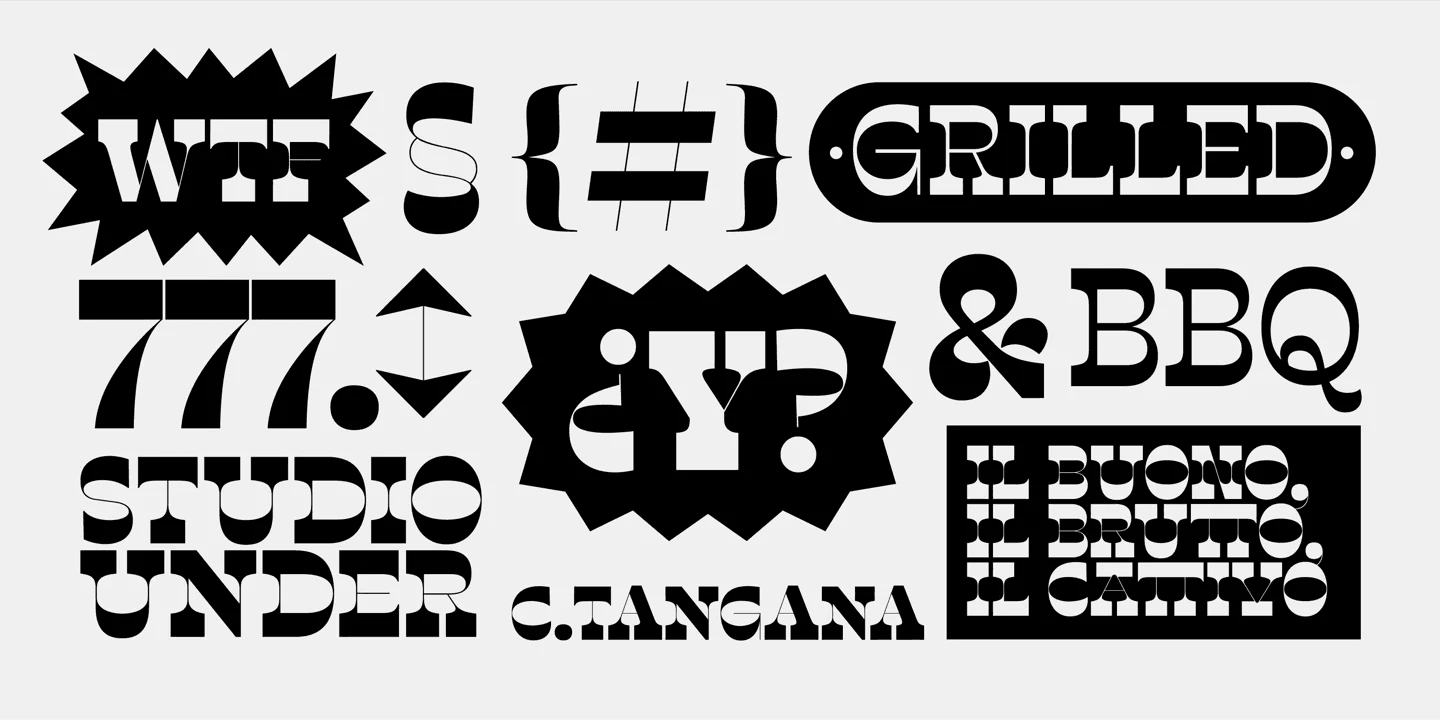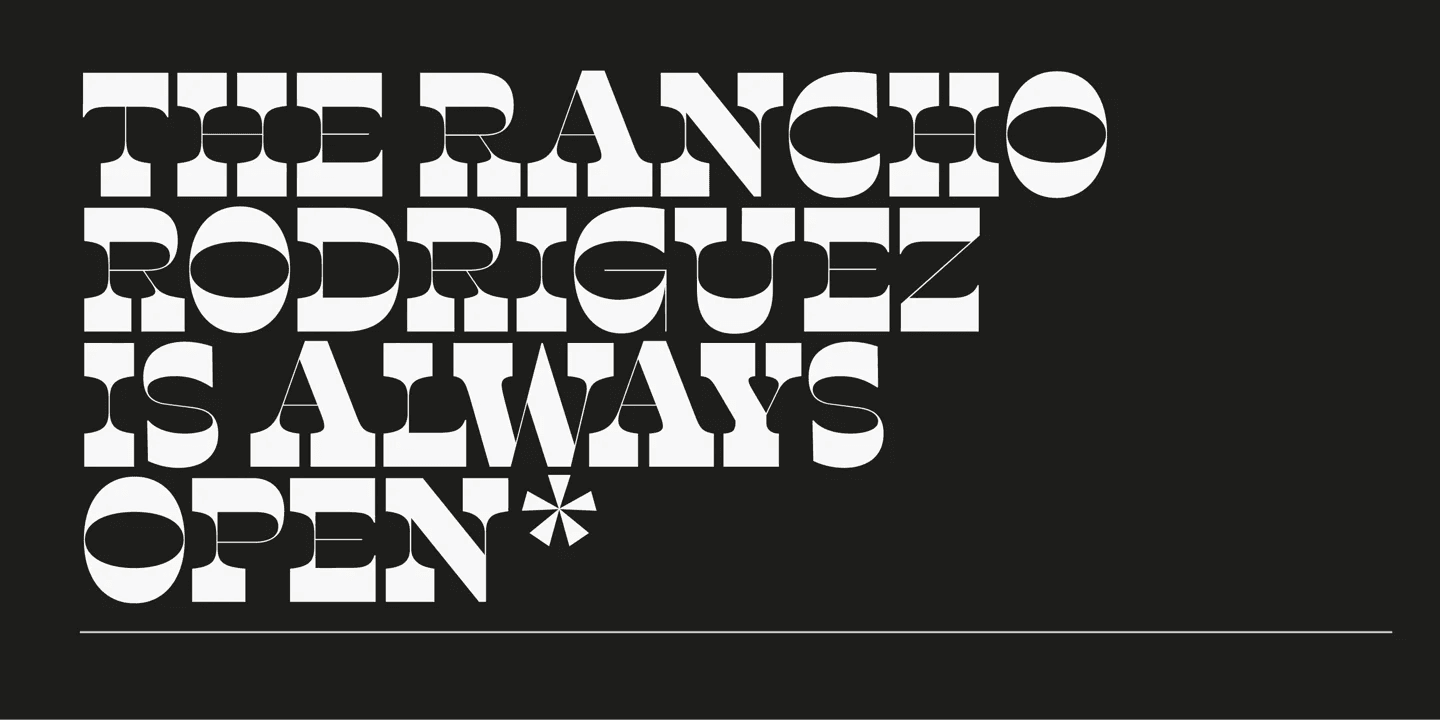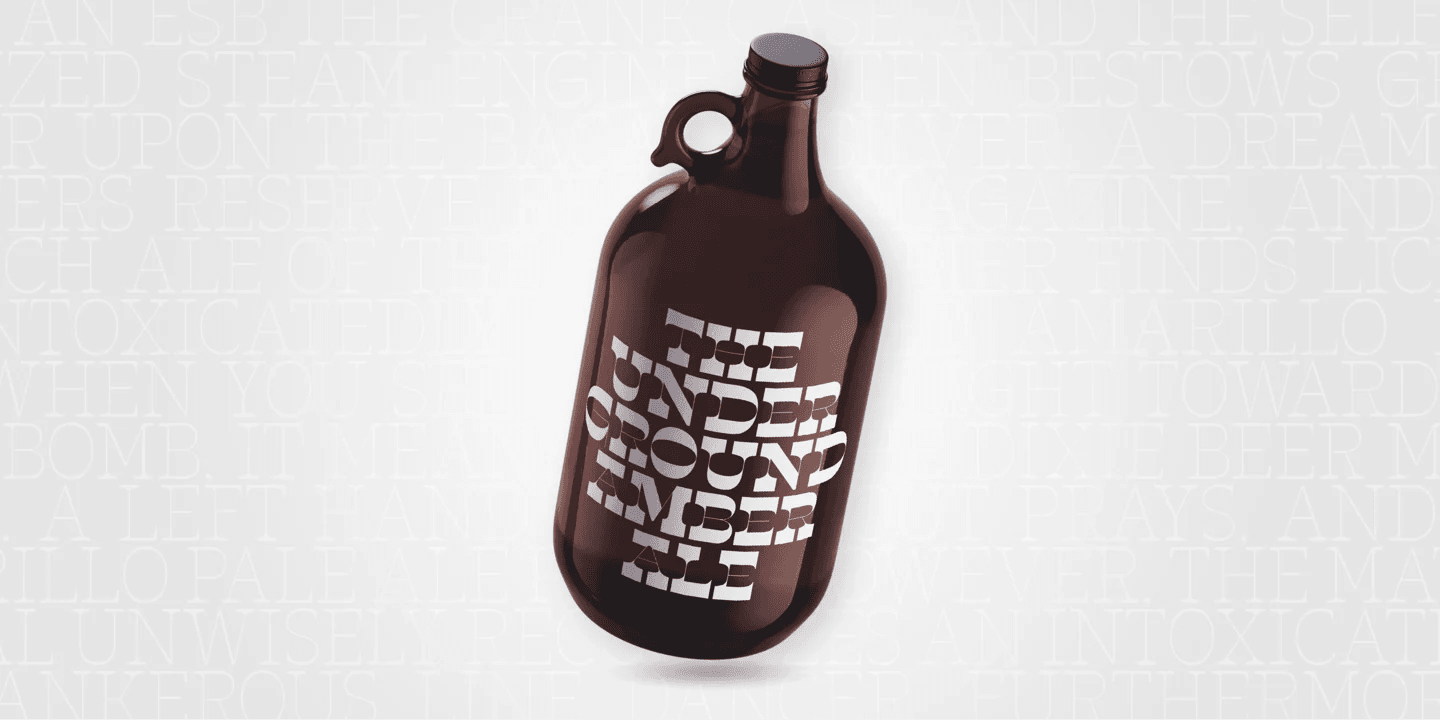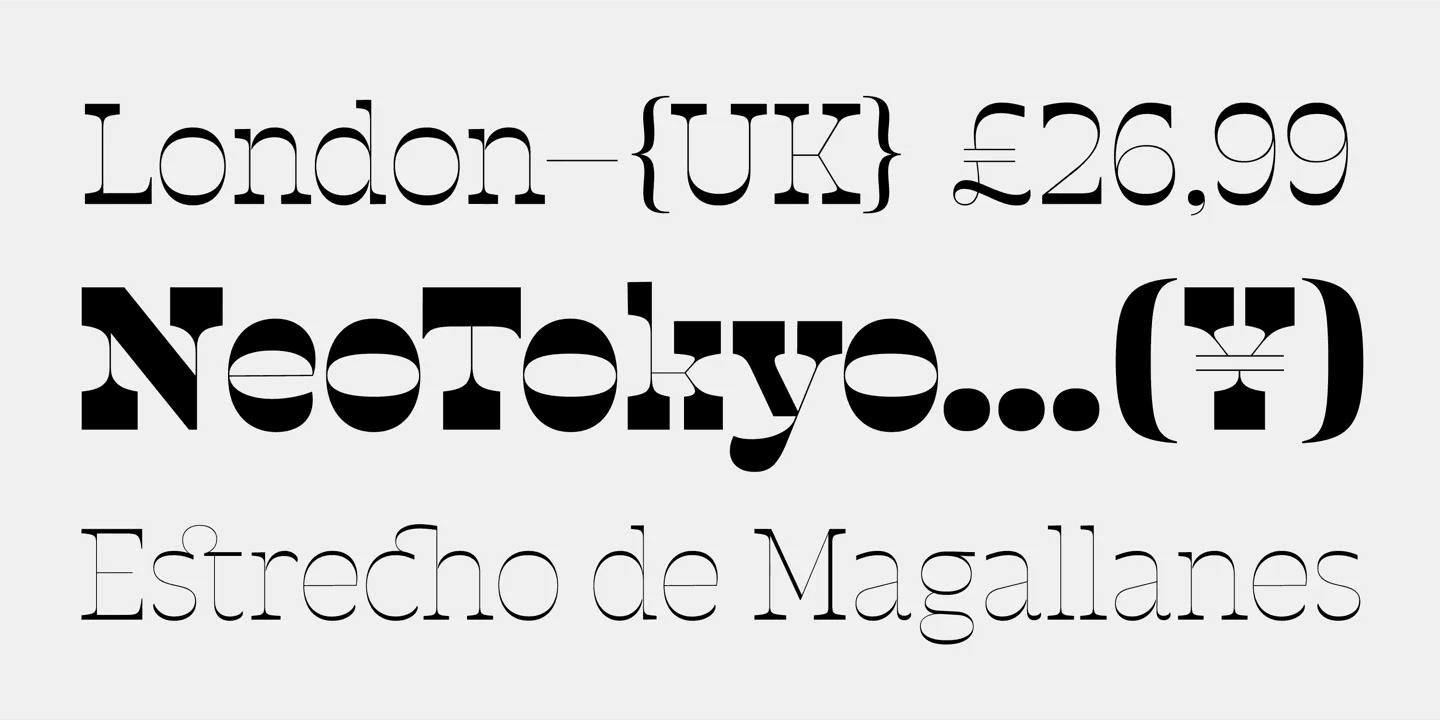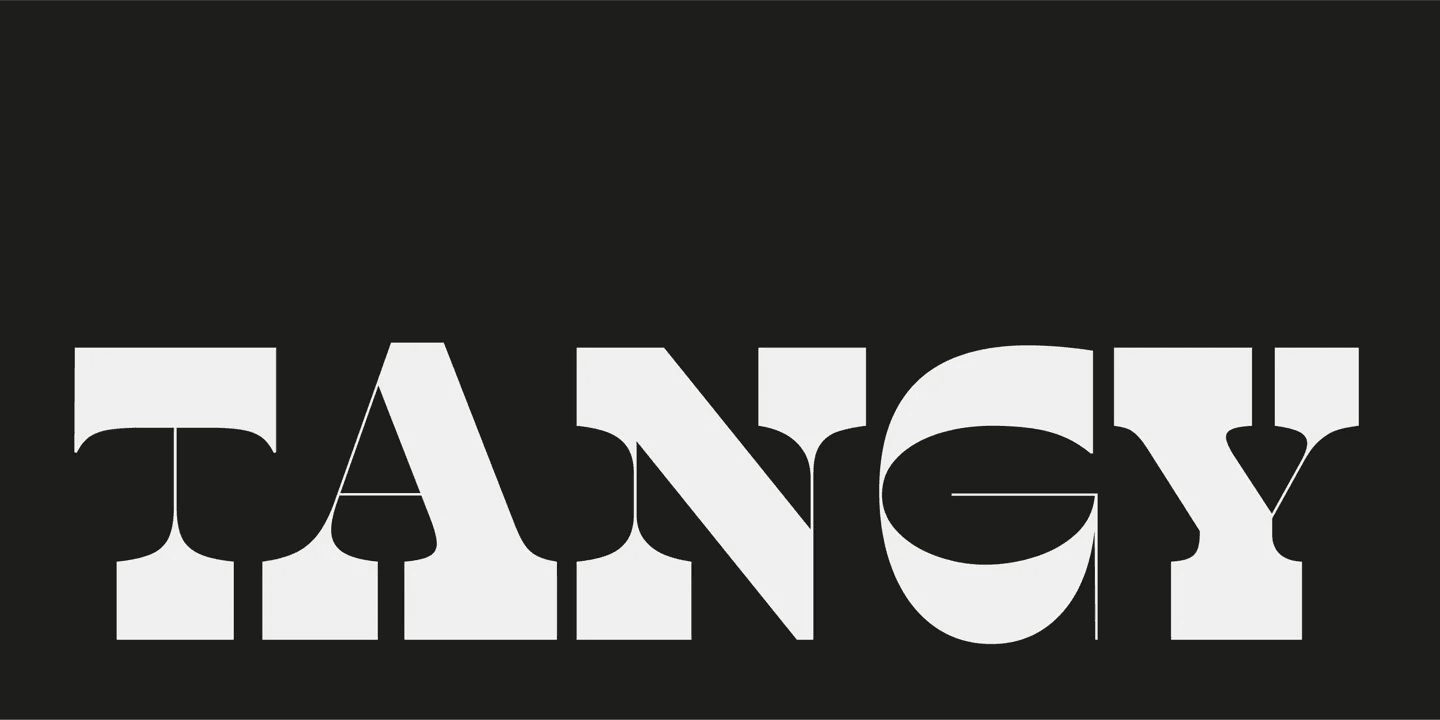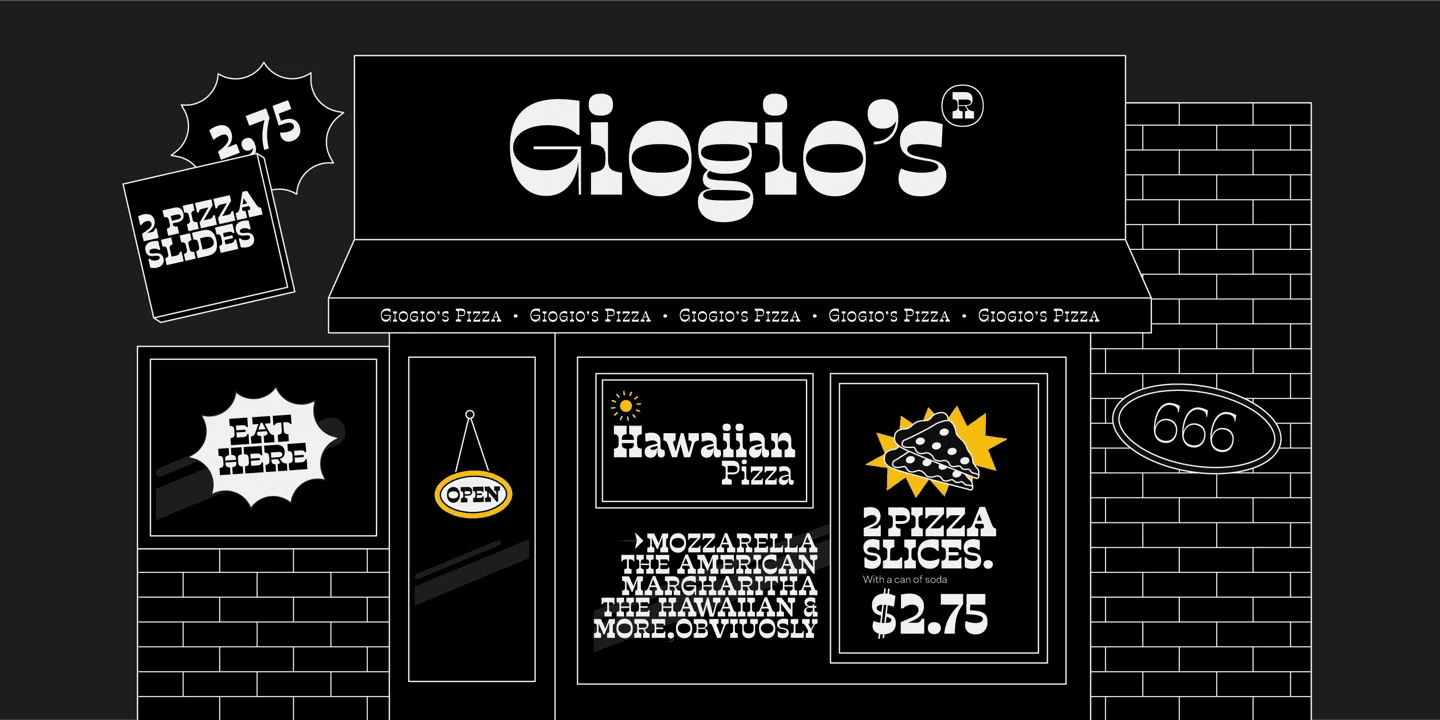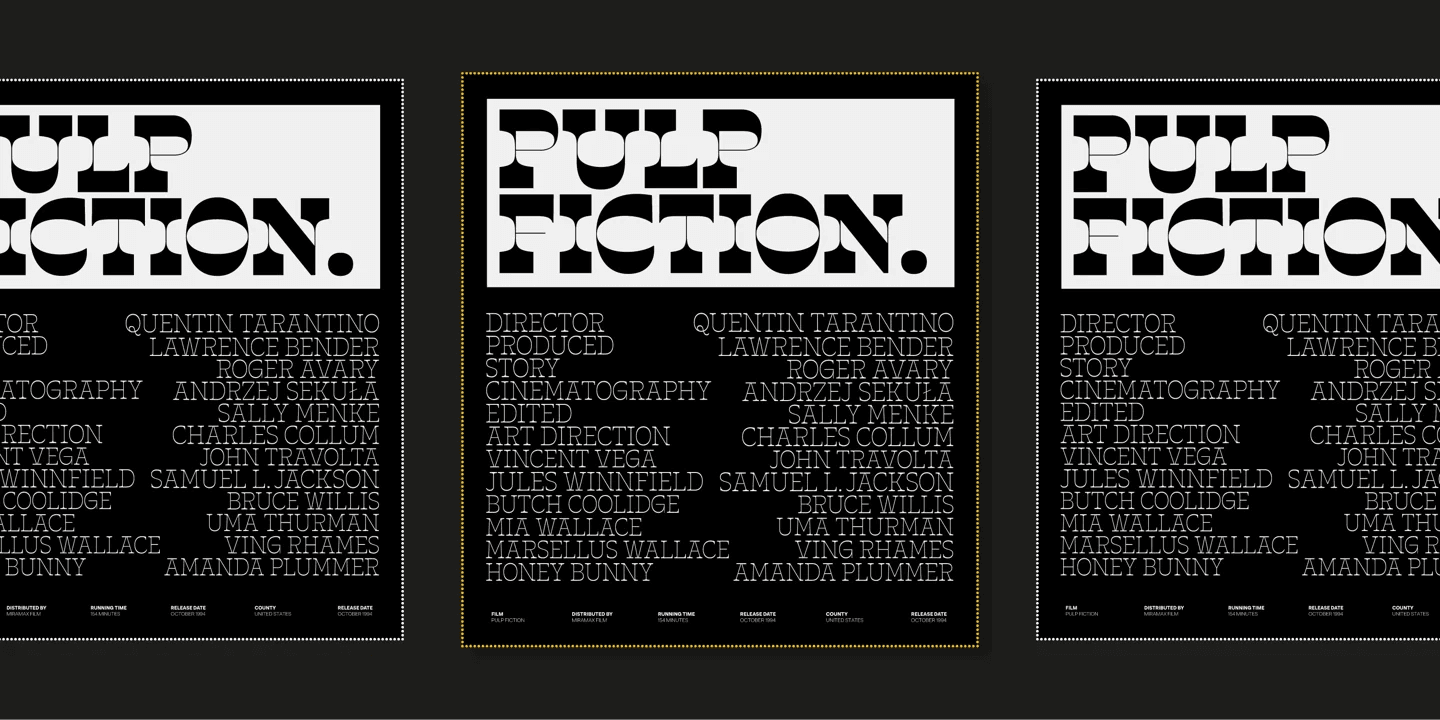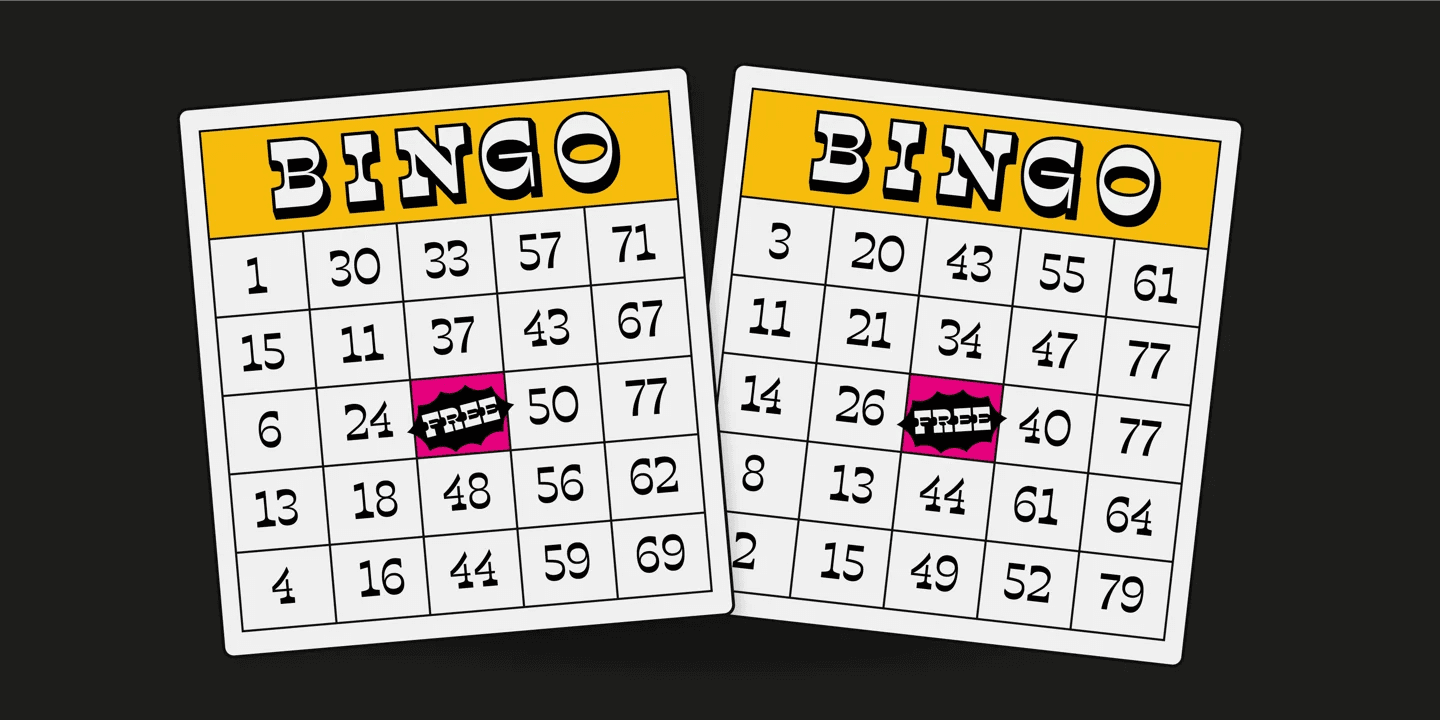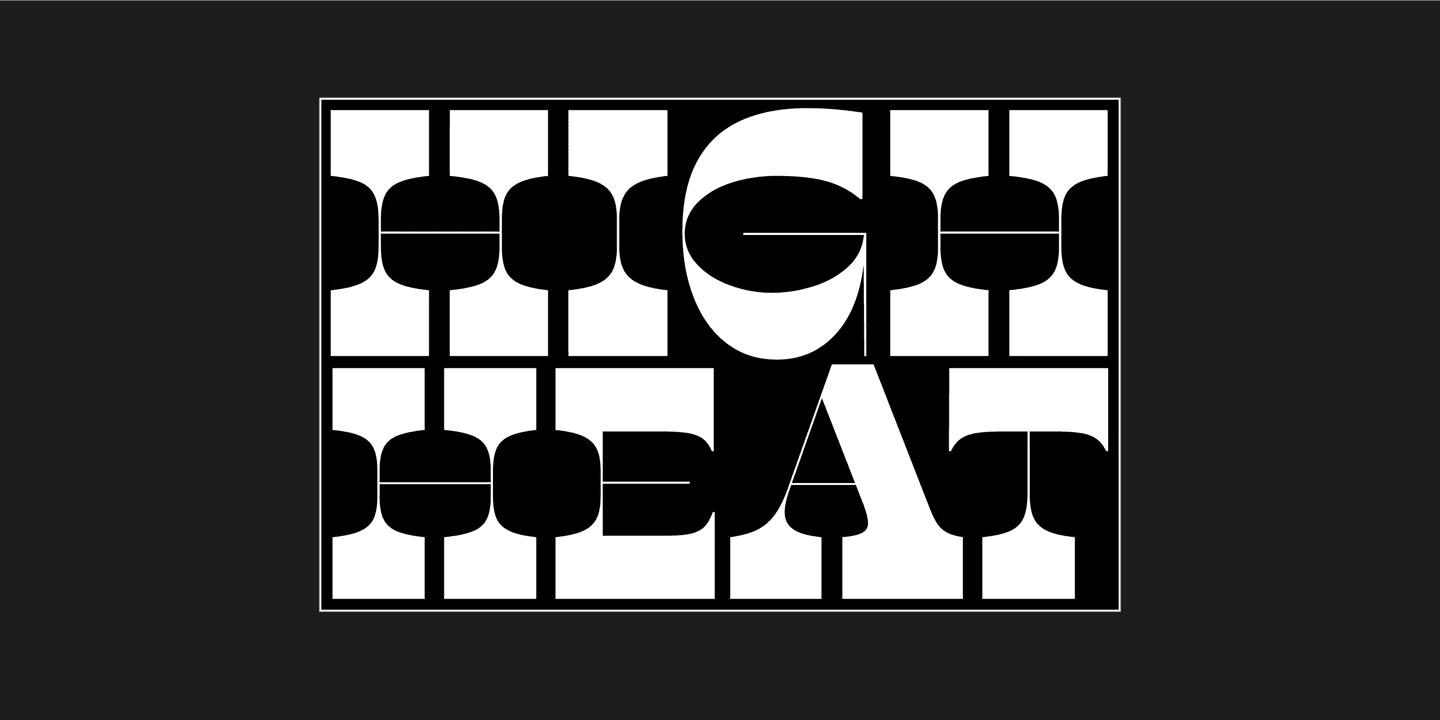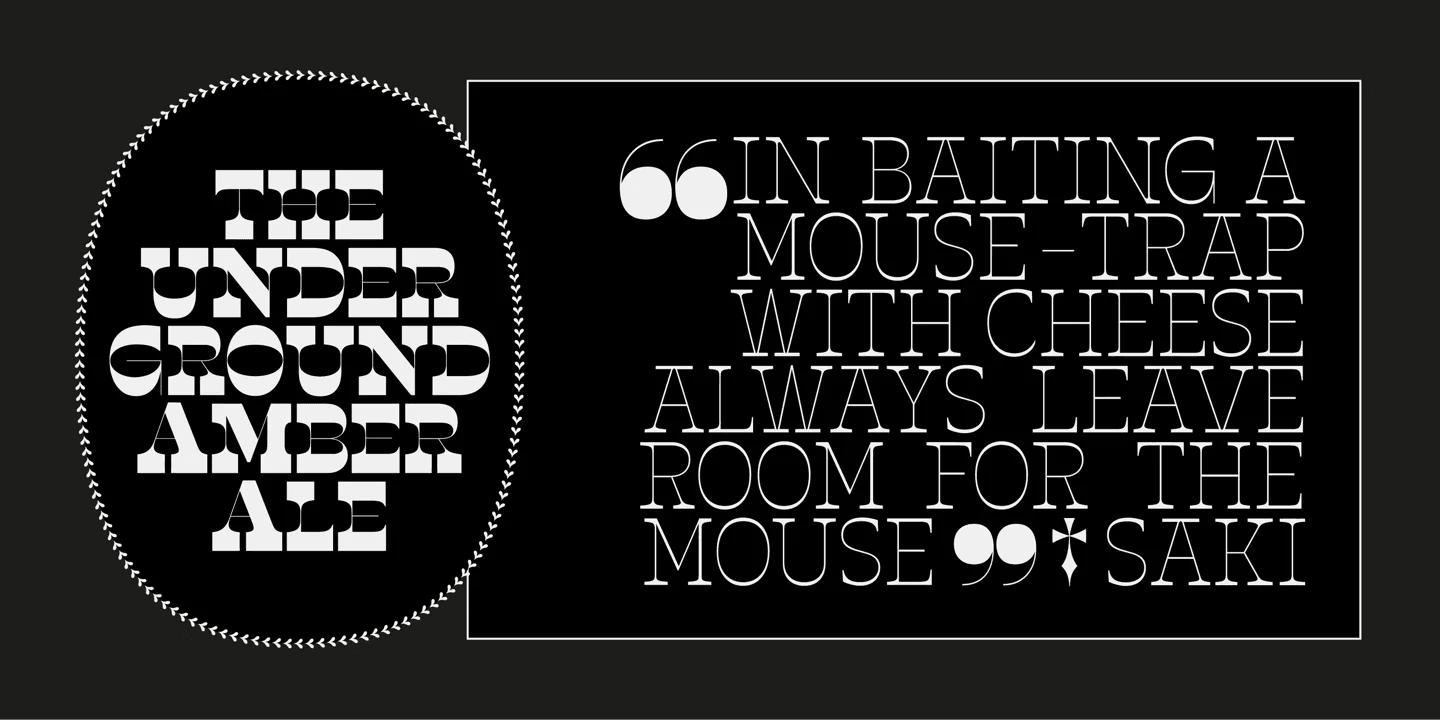
Munchies là một bộ font chữ slab-serif tương phản ngược. Lấy cảm hứng từ khối lượng và kích thước của các khối gỗ ép chữ thế kỷ 19 và ngôn ngữ Caslon của Ý.
Munchies có 12 biến thể, từ Heavy đến Thin, với các tùy chọn opentype trong một bộ bao gồm chữ hoa, chữ thường, chữ hoa nhỏ, chữ ghép và các chữ cái thay thế (A, M, N, V, W, &, Mũi tên, *).
Munchies được chia thành hai phân họ: Normal và Display. Phong cách Normal có vẻ ngoài gợi nhớ đến các áp phích phương Tây, trong khi phong cách Display có sự tương phản đến cực điểm. Cả hai phong cách cũng có sẵn trong phiên bản Variable.
Sự tương phản ngược làm cho nó trở thành một kiểu font chữ trông thú vị và nổi bật, nổi bật trong mọi ngữ cảnh. Hoàn hảo cho tiêu đề, thương hiệu đậm hoặc hoạt ảnh như kiểu chữ động.